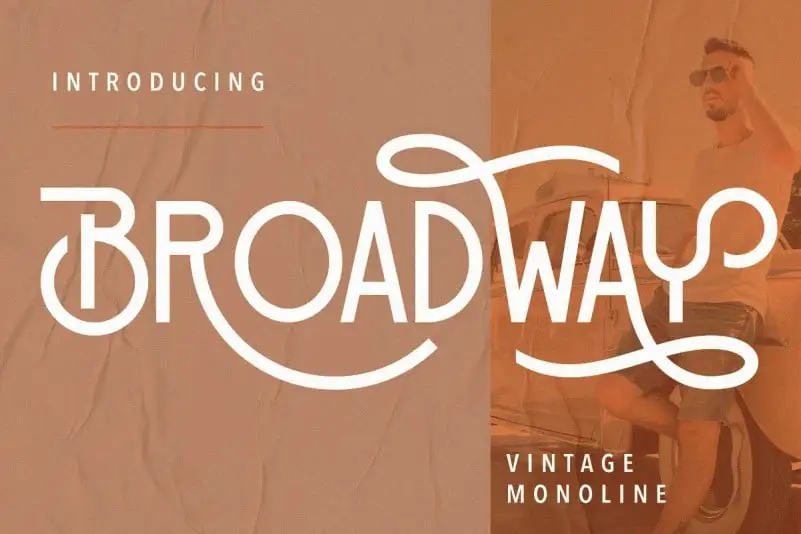
Broadway Display Font – Download Grátis
A Broadway Display Font é uma tipografia sans serif que remete aos anos 1920 e 1930, época dos famosos espetáculos de Broadway nos Estados Unidos. Ela foi desenvolvida para oferecer um estilo clássico e versátil ao design, com letras maiúsculas robustas e formas elongadas que dão a ela um toque vintage e sofisticado. Esta fonte é perfeita para aplicativos de marca como logotipos e identidades visuais corporativas, oferecendo um contraste interessante em layouts modernos e clean. Composta especialmente para designers buscando uma tipografia clássica que também se adapte bem a elementos contemporâneos, ela é ideal tanto para ambientes digitais quanto impressos, proporcionando um toque de elegância e sofisticação à qualquer projeto.